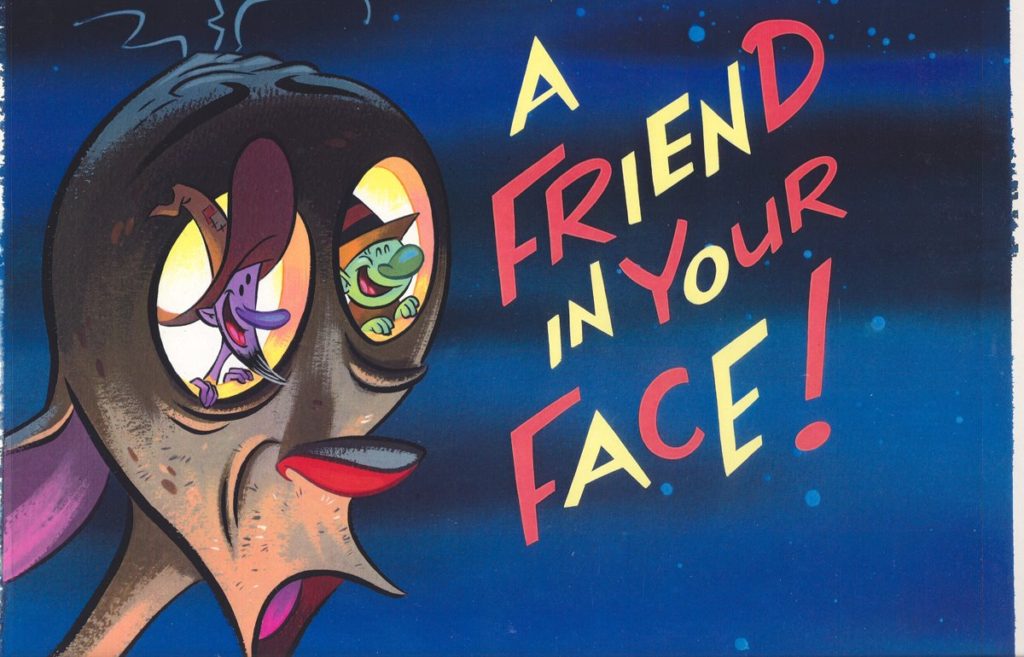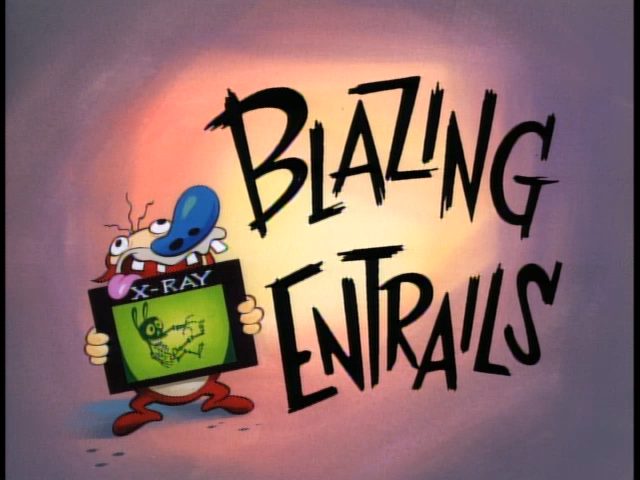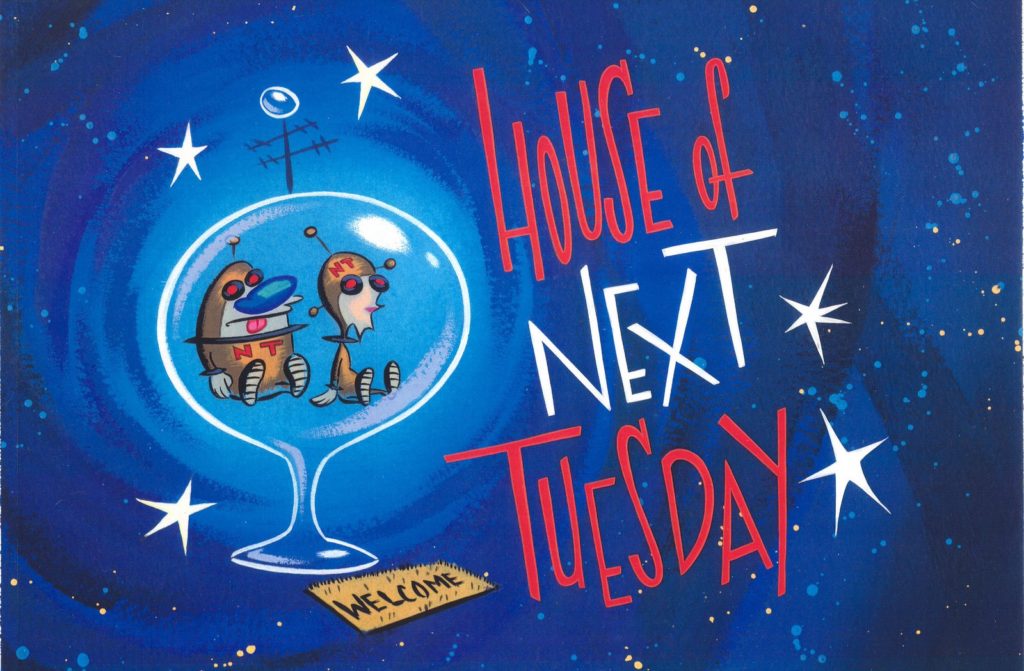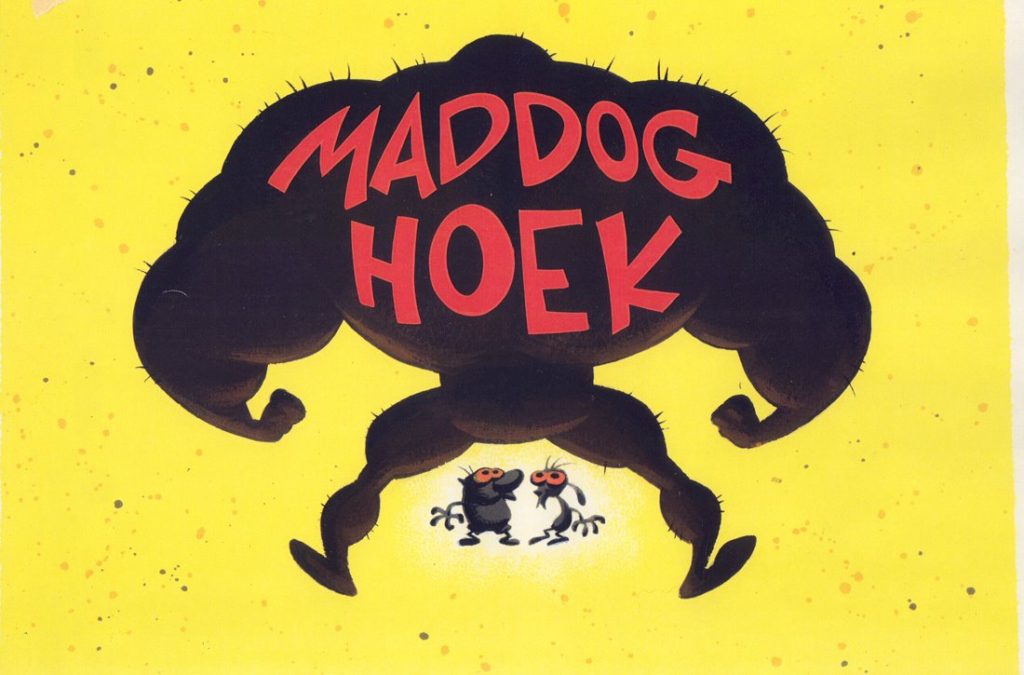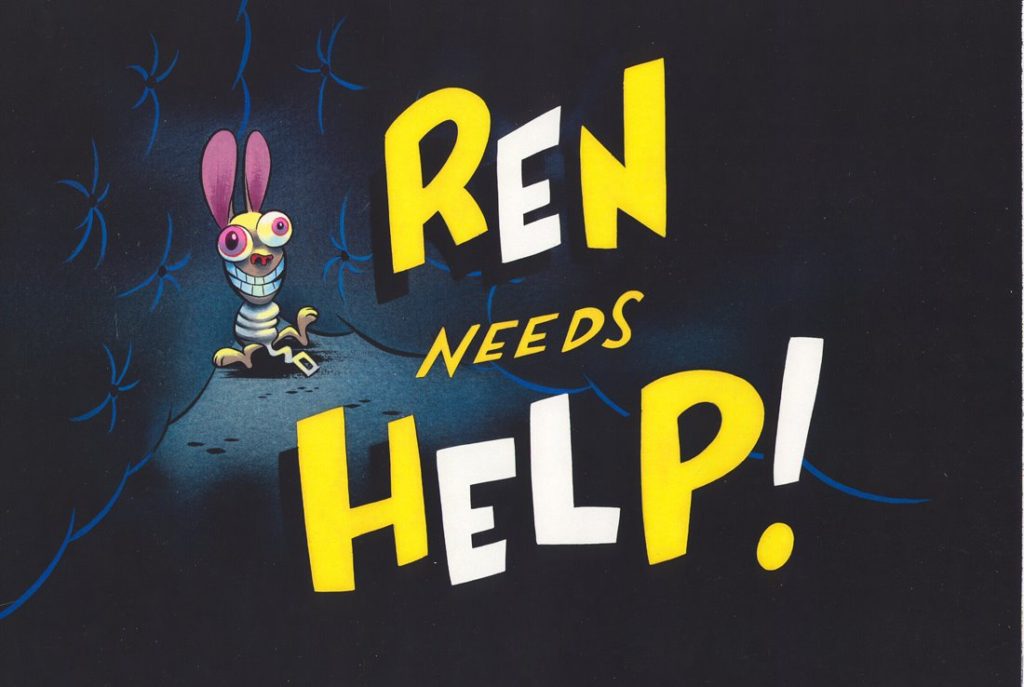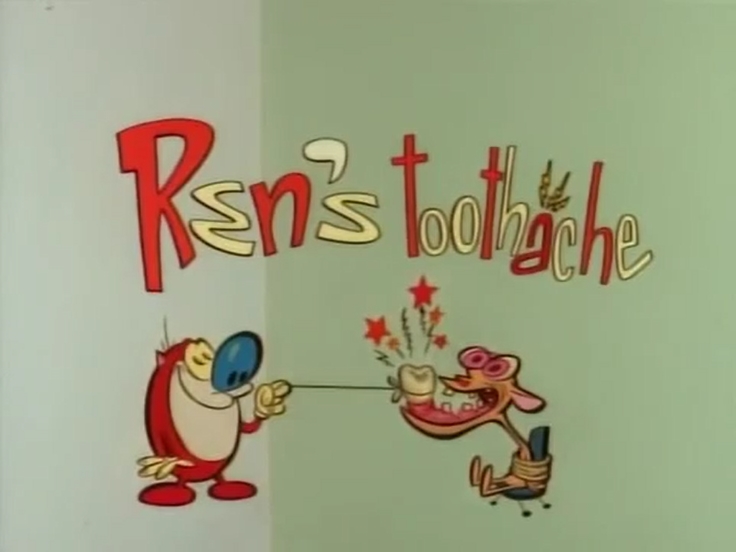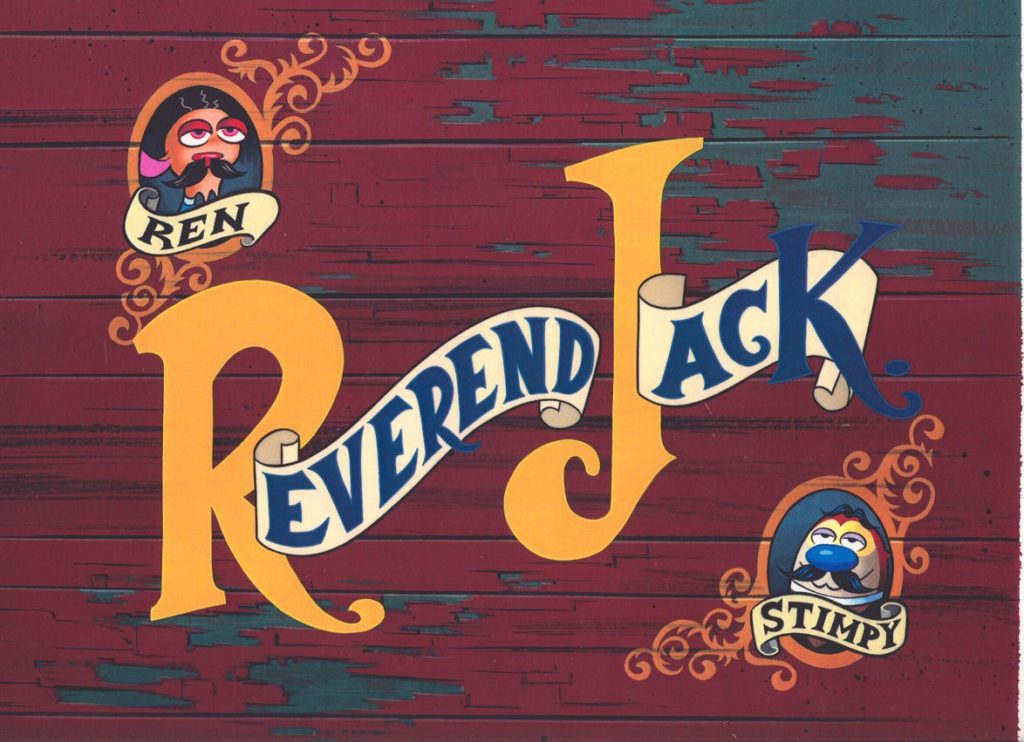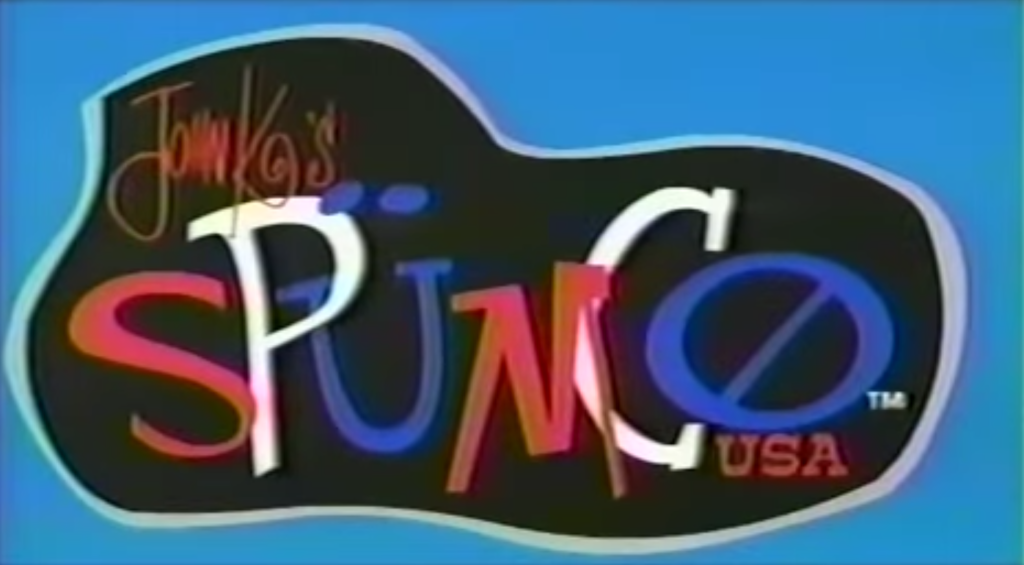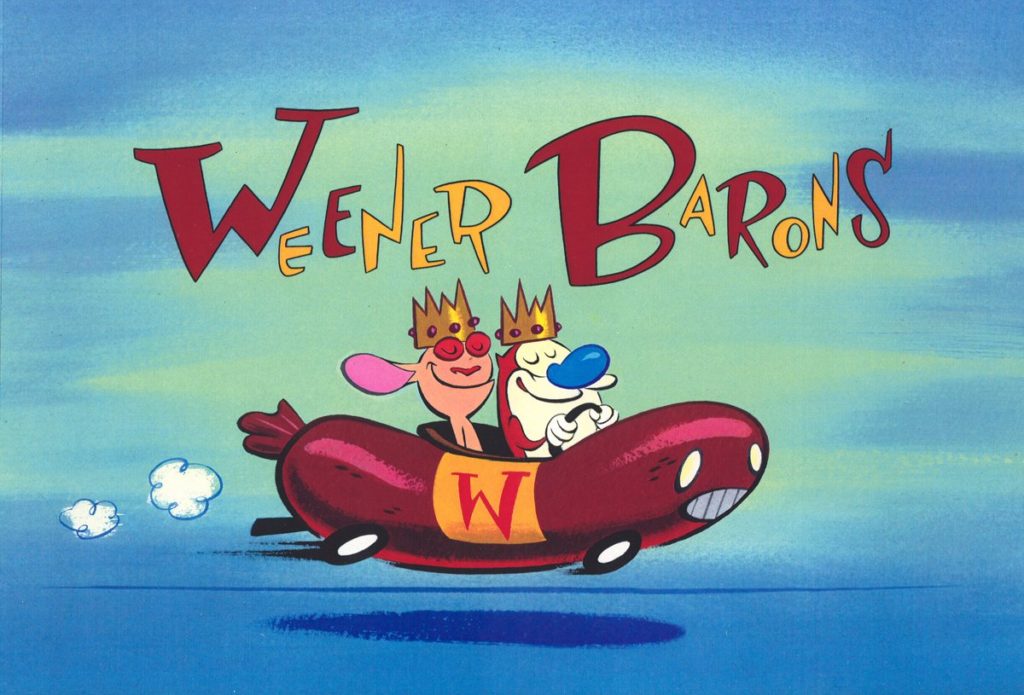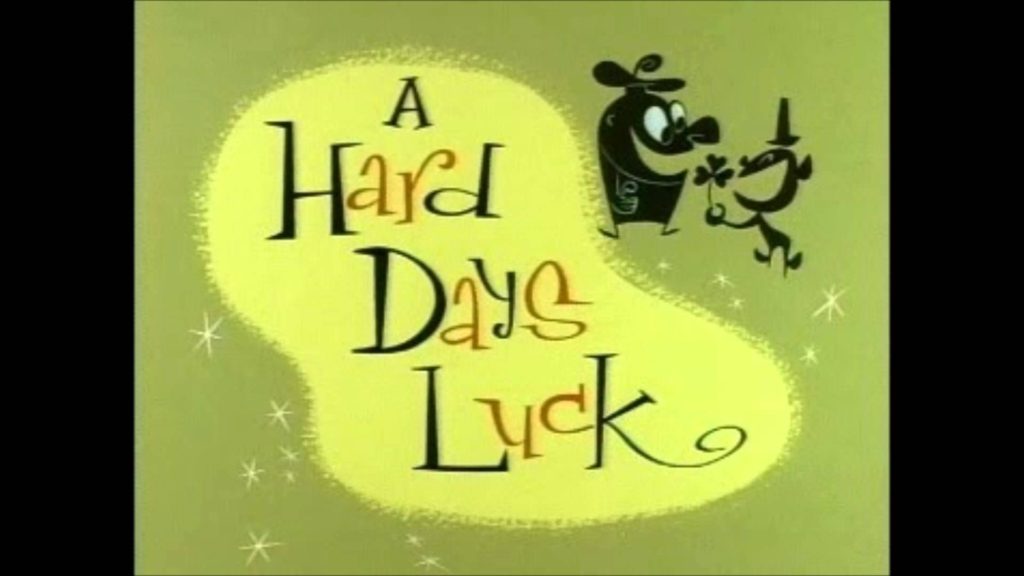
Me encanta Ren y Stimpy. Cuando era transmitido hace unos 25 años en TV, la verdad no los apreciaba tanto como los aprecio ahora. Hoy en día me parece la caricatura definitiva de una generación y el cambio que necesitaba la animación en su momento. Apartando las connotaciones sexuales de nuestros protagonistas, Ren &Stimpy es, desde lejos, una clase de arte y animación. Es una mezcla perfecta entre Hanna-Barbera, la UPA, y los mejores años de Tex Avery. La música de esta serie son clásicos europeos de principios de siglo, la animación está cuidadosamente buscada, situado en un tiempo y espacio perfecto para que nunca se nos olvide de dónde provienen. Pero hoy, les hablo de tipografía. Esta caricatura de los 90s tiene (además de los famosos, horripilantes y vomitivos close-ups”) ése elemento tipográfico que precede a esa locura animada llamada Ren y Stimpy creada por el genio de John Kricfalusi, avanzado a su tiempo y no siempre bien recibido por sus colegas, aquí les presento una pequeña galería de tapas de cartoon que comentaremos a continuación.
Pero antes, y como un servicio a la comunidad curiosa y en un afán de colaborar con el intelecto (además que no nos vamos a entender mucho a menos que seas un font-freak como yo) les enseño esta imagen para que conozcan las partes de una fuente tipográfica:
Aquí va otra:
Ahora que estamos en contexto… comencemos!
Una belleza de título: Primero, encerrado en comillas negras, como advirtiendo una entonación forzada ¿Me entienden? “Una entonación forzada” (jajaja) Segundo, un título abierto con una minúscula y los terminales en las aes… además, nótese el relleno de la casita del perro, un cuadro blanco. Sin duda, una de mis portadas favoritas.
Para mi, considero demasiado importante el uso de la proporción en el texto: de la forma que lo dibujes, dependerá el resultado de la conexión con tu pieza, en este caso un título de cartoon. Fíjense que la “E” de “House” es idéntica a la de “Next” pero está en otro contexto y color dentro de la palabra, con la proporción de la “n”, la “x” y la “t”.
Excelente uso de la tipografía! Aquí salen varias piezas… demuestran que como en el diseño, todo es parte de la integración. Tipografía, color, forma, música, animación… este clip es un festival de todo esto ¡No se lo pierdan!
¿No les provoca ver esta caricatura?
Una fuente delgada, bien vintage y acompañada de esas formas irregulares tan propias de Kandinsky más la ilustración en siluetas, es una demostración que Kricfalusi y su equipo sabían exactamente lo que estaban haciendo.
Divertido uso de los Serifs! Me encanta.
Locura visual, anarquía y desorden. Pero todo en perfecta armonía.
Disfruto mucho la “anaraquía” de Ren y Stimpy. Pienso que si en “Ren” tenemos la regla “amarillo-blanco-amarillo” en “Help” debería ser lo mismo… pero no pasa. El “needs” tiene personalidad propia que hace contraste con el resto del texto. Trazos delgados, menos es más. Diseño.
Una de las portadas diseñadas por el Co-Creador de la serie, el gran Bob Camp. Aquí puedes conocer más de este animador y director, fundador de Spumco, la compañía que hacía éstos cartoons. Para que vean que no es juego el tema de la tipografía con estos tipos, miren el logo de la empresa:
Maravilloso. (Éste es el episodio donde Stimpy se enamora de su propio “gas”, “Olorín” ¿Recuerdan?)
No creo que en la historia de animación existan portadas más transgresoras que éstas…
Classic Ren & Stimpy 🙂
Una de mis favoritas. la “S” con el aguijón exagerado y el asta desproporcionado nos dan una sensación más que musical, con esas ondas y el gran peso que tiene. Fíjense cómo la “H” tiene serif y a la “K” le falta. Atender el serif de la “N” todo un espectáculo para cerrar la palabra.
La tipografía habla por sí sola. “Scostman” tiene una intención distinta a “Space” que está dibujada en proporción. ¡Ya quiero ver ese episodio de nuevo!
Por el genial Bob Camp!
La tipografía, en conjunto con los demás elementos de la pieza, en este caso una portada de cartoon, está en armonía, aún cuando pareciera un desorden. Cada elemento conecta con el otro, como la expresión de Stimpy y sus dientes torcidos, con el brochazo inminente de las tipos. Uno de los “hombros” de la letra “B” es más grande que el otro, como si se tratase de una explosión: viene de abajo hacia arriba. Los vértices están definidos por el final de la brocha del pincel, y no olvidemos el detalle “artístico” del serif en la “G” y la “S”. Genial.
Aquí vemos un ejercicio magistral de proporciones y serifs. Miren cómo la “o” es realmente pequeña al lado de la “K” de Kricfalusi. La “B” pareciera que sostiene a la “o” y con la otra letra forma una divertida integración. Noten cómo la “C” abraza por completo a la letra “a” y si se fijan bien, tampoco hay respeto por la continuidad, porque no todas las letras están del mismo color.